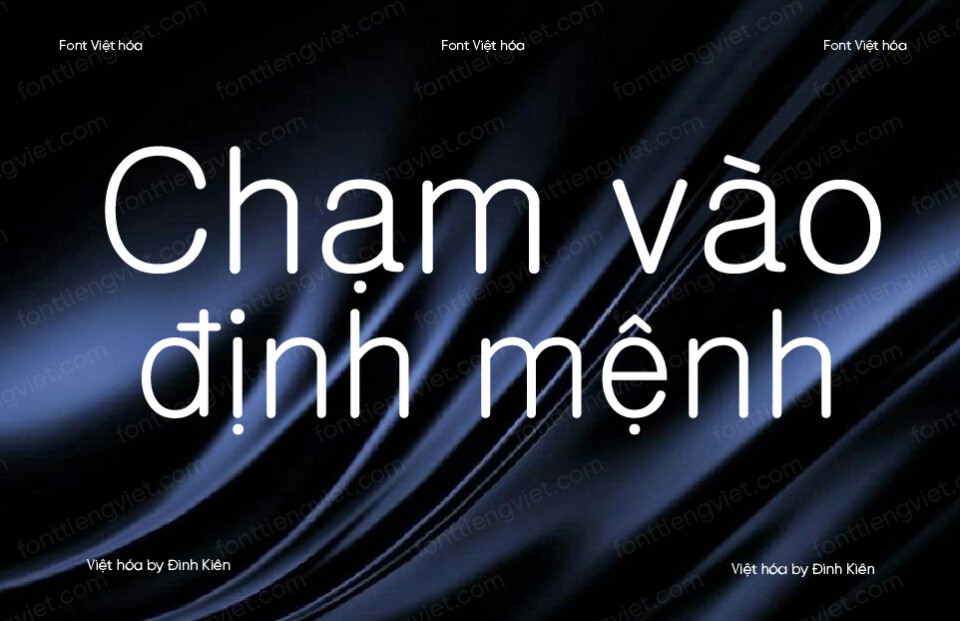
Giới thiệu về Font Việt hóa UTM Gulim
Trong môi trường giáo dục, việc lựa chọn Font Chữ phù hợp đóng vai trò quan trọng trong việc truyền tải kiến thức. Font Việt hóa UTM Gulim là một trong những bộ phông chữ được ưa chuộng nhất nhờ thiết kế không chân đơn giản, hiện đại và cực kỳ dễ đọc. Được phát triển dựa trên phong cách chữ Hàn Quốc đặc trưng, phiên bản Việt hóa này giúp các bạn học sinh và thầy cô giáo trình bày bài giảng, báo cáo một cách khoa học. Sự rõ ràng của từng nét chữ giúp giảm mỏi mắt khi đọc tài liệu dài trên màn hình máy tính hoặc giấy in.
Ưu điểm nổi bật của Font Việt hóa UTM Gulim
Thiết kế tối giản và chuyên nghiệp
Font Việt hóa UTM Gulim sở hữu đường nét tròn trịa, cân đối, tạo cảm giác thân thiện nhưng vẫn giữ được sự nghiêm túc cần thiết. Đây là lựa chọn hoàn hảo cho các bài kiểm tra, slide thuyết trình hoặc các thông báo trong nhà trường. Khả năng hiển thị tốt ở nhiều kích thước khác nhau giúp bộ phông này trở nên đa năng trong mọi tình huống thiết kế cơ bản.
Tương thích tốt với bảng mã Unicode